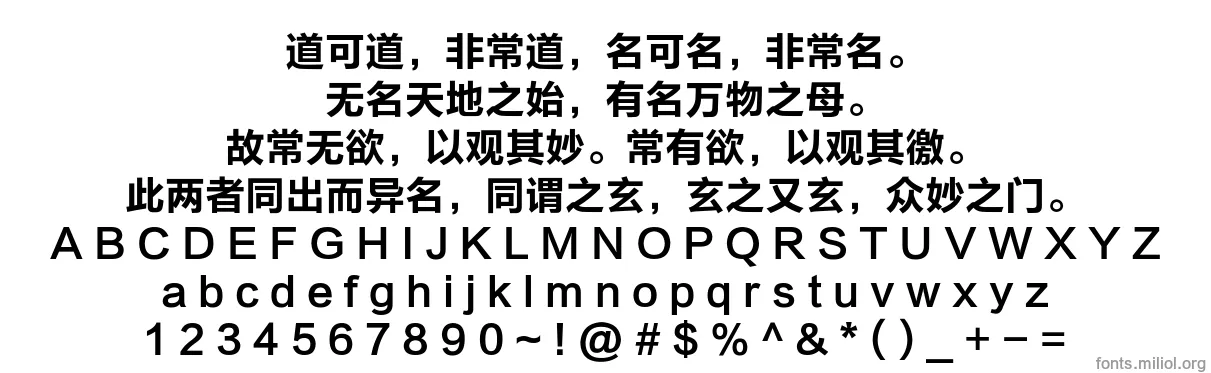
**方正兰亭粗黑简体字体简介**
方正兰亭粗黑简体(FZLanTingHeiS-B-GB)是一款由方正字库设计的中文字体,属于兰亭黑系列中的粗黑变体。其笔画粗壮有力,结构严谨,兼具现代感和视觉冲击力,适合用于标题、广告、海报等需要突出显示的场景。字体风格稳重而不失灵动,在保持黑体简洁特征的同时,通过细节处理增强了辨识度。
作为GB2312标准字符集的字体,它覆盖了常用汉字及符号,兼容性良好,可满足印刷、数字媒体等多场景需求。方正兰亭粗黑简体的设计兼顾实用性与美观性,是设计师和排版工作者的优选字体之一。使用时需遵守版权规定,确保合法授权。